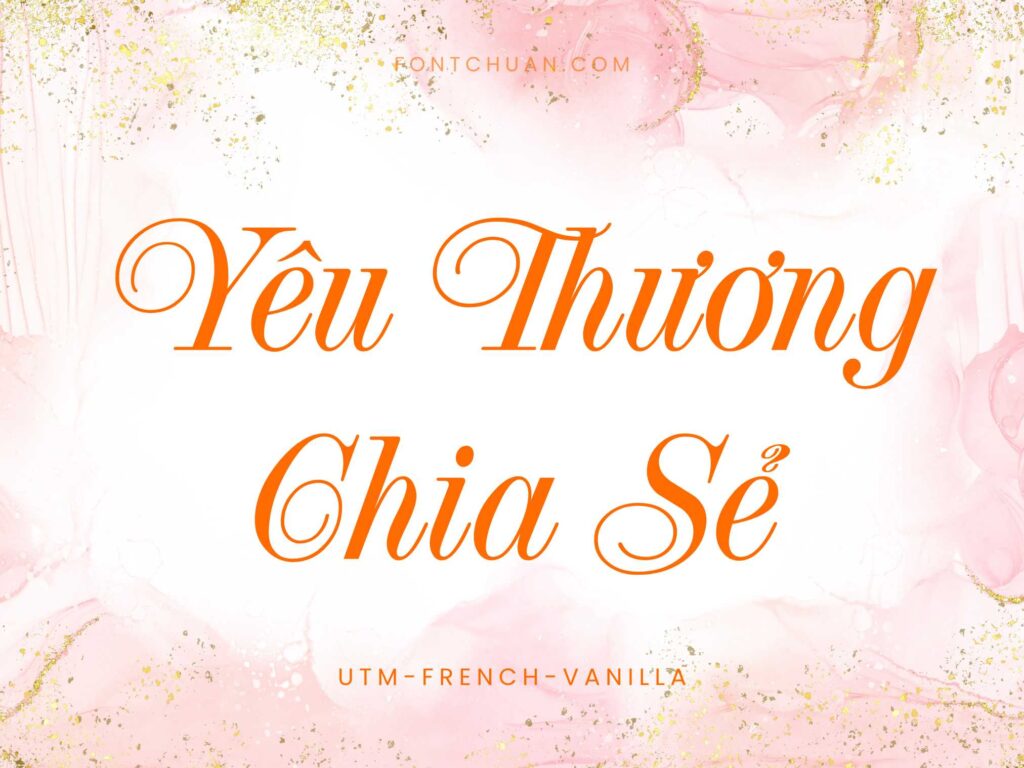
Font UTM French Vanilla Việt Hóa là một kiểu chữ serif mang phong cách cổ điển, thanh lịch và sang trọng. Với đường nét mềm mại, tỷ lệ chữ cân đối và độ thoáng rộng, font này là lựa chọn hoàn hảo cho các thiết kế mang phong cách quý phái, tinh tế và chuyên nghiệp.
Font này đã được Việt hóa để hỗ trợ đầy đủ tiếng Việt bởi Thiên Minh, ngoài ra còn hỗ trợ hơn 200 ngôn ngữ khác. Thành viên của Font Chuẩn đã sưu tầm và chọn lọc font này nhằm đáp ứng nhu cầu của người dùng trong thiết kế và ứng dụng thực tế. Font có đặc điểm nổi bật với kiểu chữ thanh lịch, phù hợp với các dự án như thiết kế logo, bìa sách, bao bì sản phẩm và nhiều lĩnh vực sáng tạo khác.